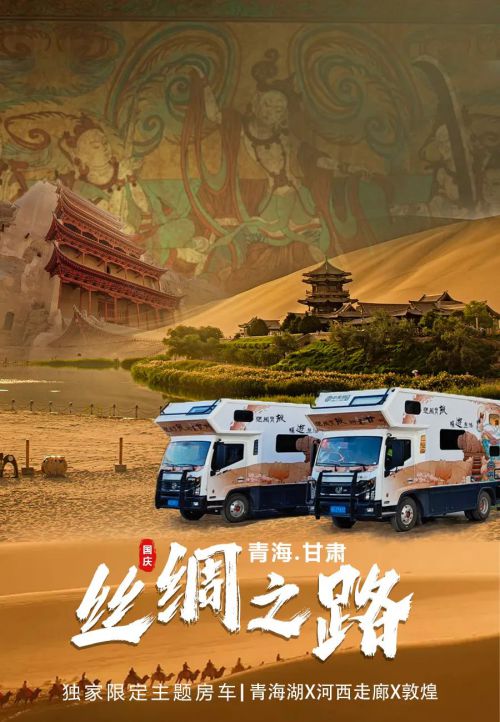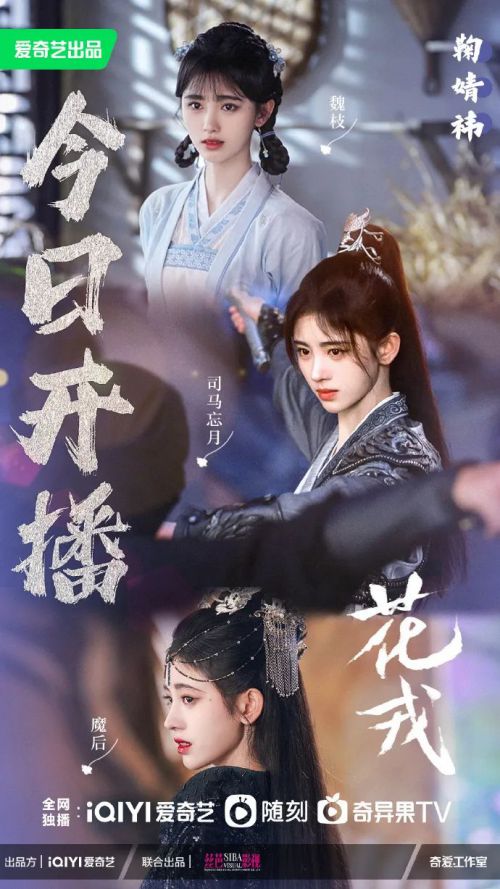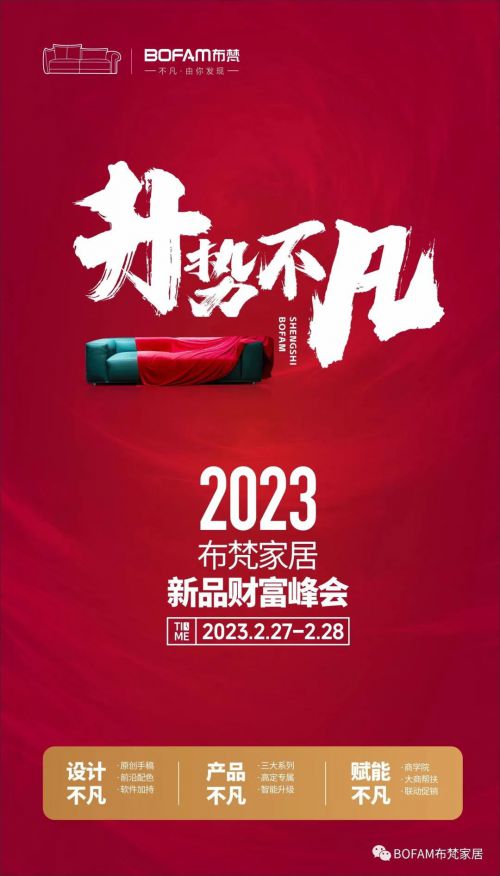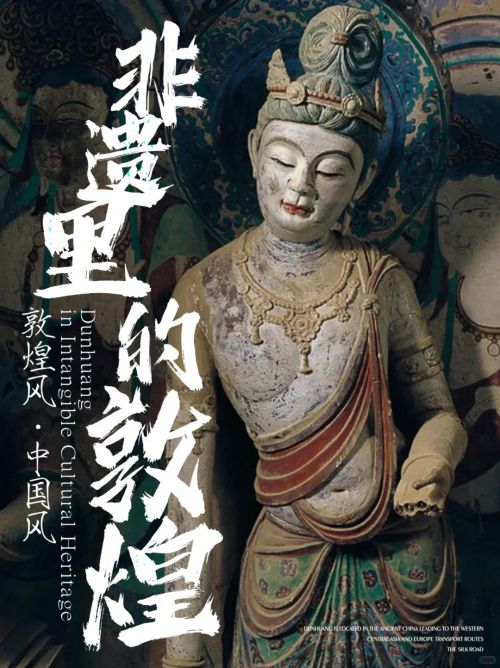
点字浩魂
字库品牌: 点字库 >
点字浩魂是点字库打造的一款中国风力量感手写体,以复古笔触碰撞现代设计,尽显豪放不羁的书写魅力。作为手写体家族中的独特存在,其字形方正稳健,重心居中平衡,中宫宽博舒展,带来大气开阔的视觉张力。笔型以利落直角勾勒,方头笔画刚劲如刀刻,粗细均匀的线条中暗藏飞白肆意的笔触,锋芒毕露却不失结构严谨——断开的笔画连接设计,既保留手写的随性洒脱,又让字符轮廓更清晰易读。 从复古海报标题到力量感品牌LOGO,从国风包装设计到文化主题宣传,点字浩魂凭借“中国风+豪放”的双重气质,总能以坚挺笔触演绎东方美学。作为会员商用授权字体,它不仅满足设计创意需求,更以“放浪不羁却自有筋骨”的独特个性,成为传递态度与文化的优质视觉载体。